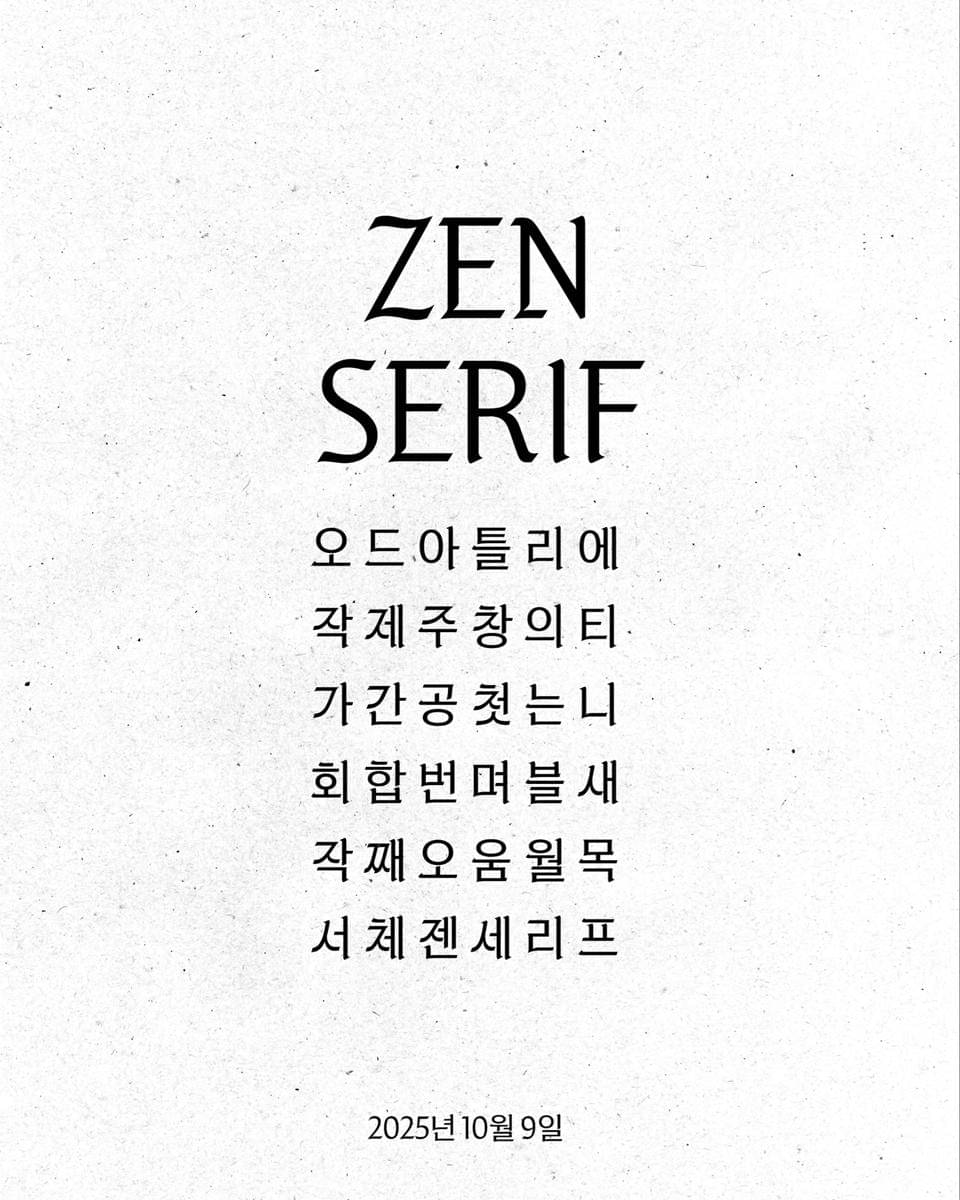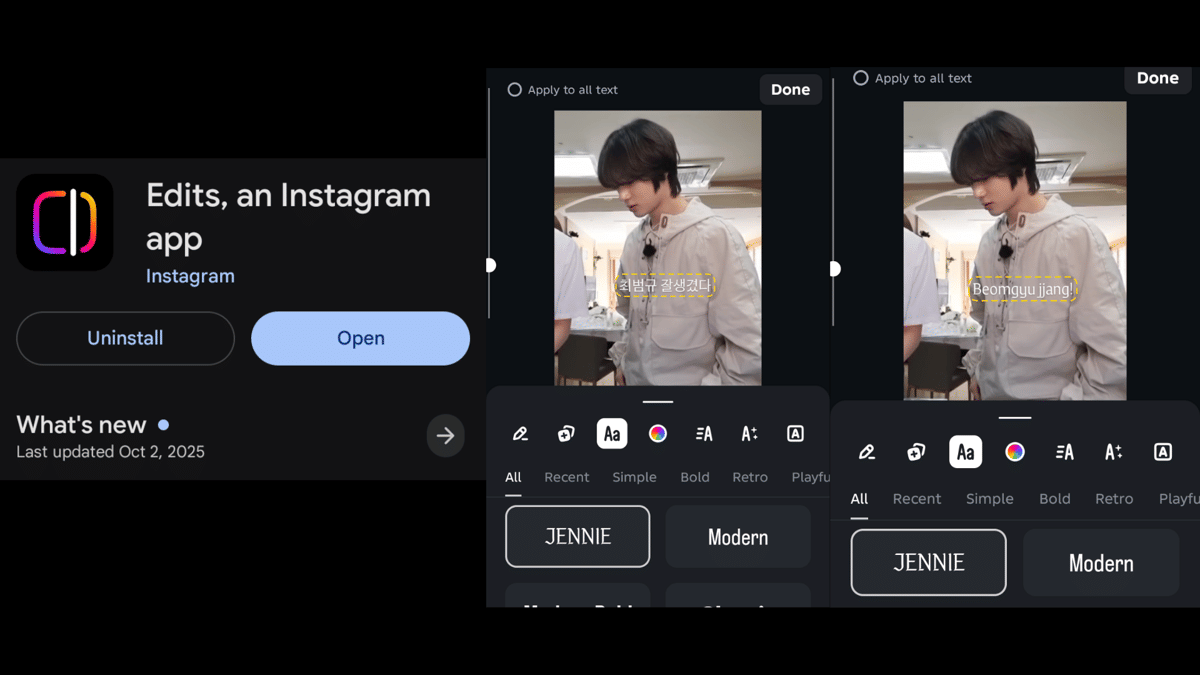
Jennie BLACKPINK Rilis Font Zen Serif di Hangul Day, Ini Cara Pakainya
Jennie BLACKPINK merilis font Zen Serif untuk mempromosikan keindahan huruf Korea
Font ini dapat digunakan dalam aplikasi editing seperti Instagram Edits, baik untuk huruf hangul maupun alfabet
OA Entertainment merilis font secara gratis sebagai peringatan Hangul Day, bentuk cinta Jennie pada budaya Korea
Jennie BLACKPINK mengejutkan penggemar dengan merilis font khusus. Odd Atelier, agensi Jennie, mengumumkan Zen Serif sebagai nama font tersebut pada Kamis (9/10/2025) dini hari.
Perilisan font ini dilakukan dalam rangka merayakan Hangul Day yang jatuh pada 9 Oktober. Yuk, simak fakta selengkapnya!
1. Nama dan makna font Zen Serif
Zen Serif (x.com/oddatelier) Jennie merilis font yang diberi nama Zen Serif. OA Entertainment memperkenalkan font tersebut untuk mempromosikan keindahan hangul atau huruf Korea.
“Zen Serif adalah font yang menciptakan kembali keindahannya dengan melepaskan diri dari norma konvensional. Kami meminimalkan fitur dekoratif, tetapi juga menghindari citra yang kaku dengan menambahkan kurva fleksibel untuk menonjolkan ciri khas seni OA Entertainment,” ujar agensi dikutip dari Korea JoongAng Daily.
3. Zen Serif dibuat untuk memeringati Hangul Day
Jennie mendominasi YouTube (Dok: KpopWiki/Fandom) Dilansir Sports Chosun, OA Entertainment merupakan agensi hiburan pertama yang merilis dan mendistribusikan font secara gratis. Agensi tersebut mengatakan, Jennie selalu ingin menunjukkan cintanya untuk Korea dan budayanya melalui beragam aktivitas yang berbeda.
Hangul Day sendiri adalah hari untuk memeringati terciptanya abjad asli dari bangsa Korea yang diciptakan oleh Raja Sejong. Pada Juli 2025, ia ditunjuk menjadi honorary ambassador untuk mempromosikan pariwisata di Seoul tahun ini.